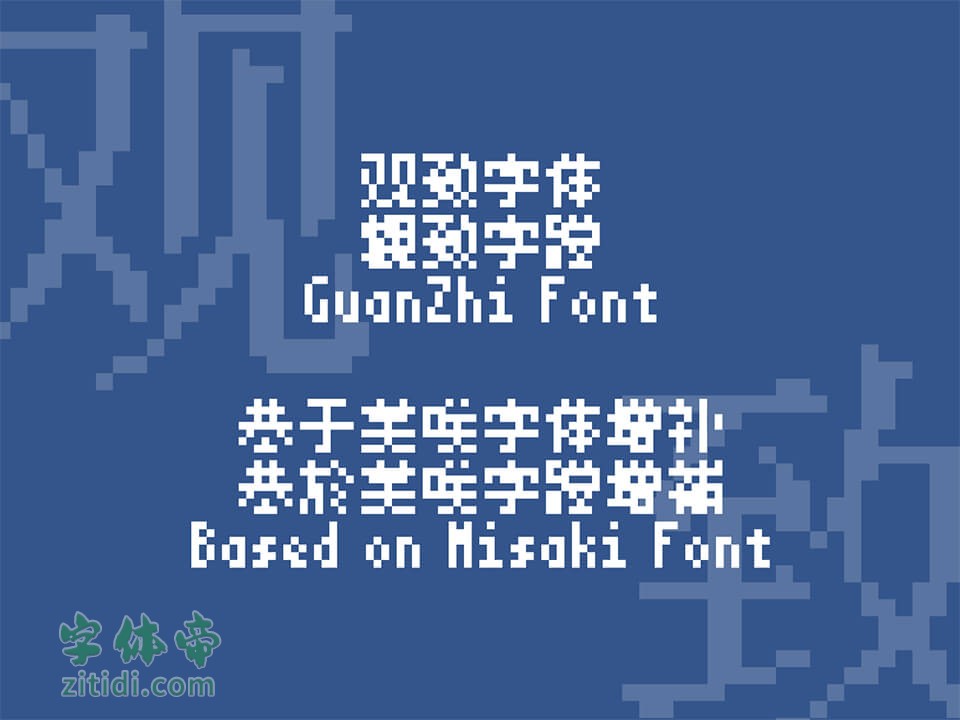
本字体是基于日本字体MISAKI做的,所以我不敢说是原创0 0
..它有7*7的一级二级汉字在里面…我补充了GB2312的汉字.
所以字符集是GB2312+日本一级二级汉字.
第一个能用的版本出来了..
接下来
○优化简体字
○向BIG5常用字进军….
=====
发现行距有问题.所以加入矢量轮廓进去..
问题解决